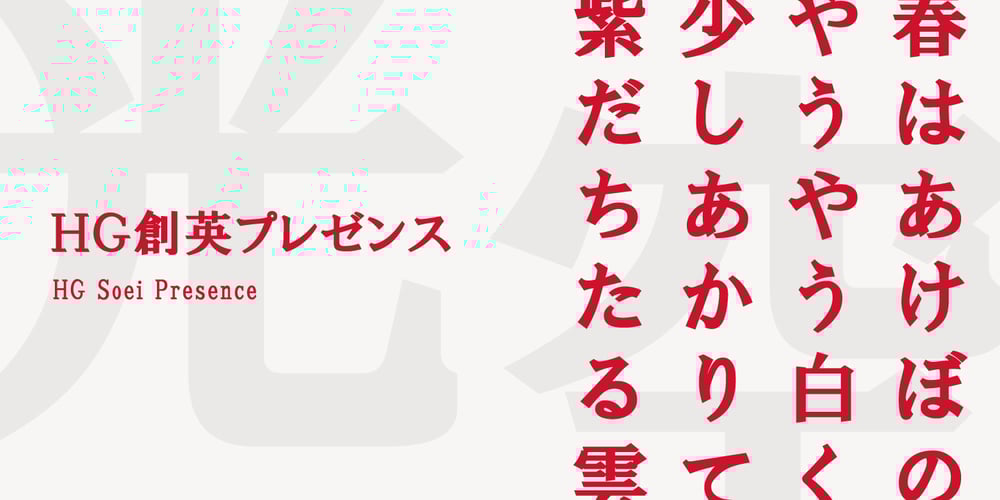
HG Soei Presence Font Family was designed by published by RICOH. HG Soei Presence contains 1 styles and family package options. HG創英プレゼンスのデザインは、創英企画。横画が太い明朝体系の書体です。データ量を少なくするため、微妙な傾きや太さの変化を避け、始筆部や終筆部の飾りや、はらいの先端部、ゲタやはね、うろこなどの形状は、できる限り、直線化したり、単純化するなどの処理を行っています。そのため、シンプルですっきりとしたデザインの書体になっています。大きなサイズで使用したほうがよいでしょう。